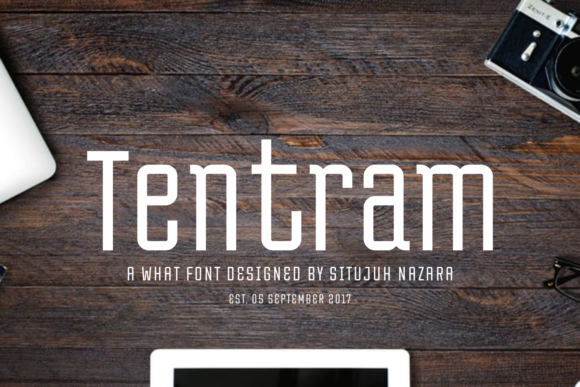
Introduzimos a Tentram Typeface! Desenhada por Hamilton, esta é uma fonte tipo sans serif com um ar retro-móbil. Ela remete ao primeiro uso da sua antiga e querida móvel descomplicada no fundo de um armário, quando finalmente a ligas para o uso depois de anos sem ser usada. A Tentram está perfeita para design digital, como aplicativos, e pode ajudá-lo a criar uma experiência de marca única. É ideal para quem busca algo mais moderno que se destaca no mundo dos fontes sans serif, oferecendo um estilo retro-móbil que vai ficar eternizado em sua próxima peça criativa.